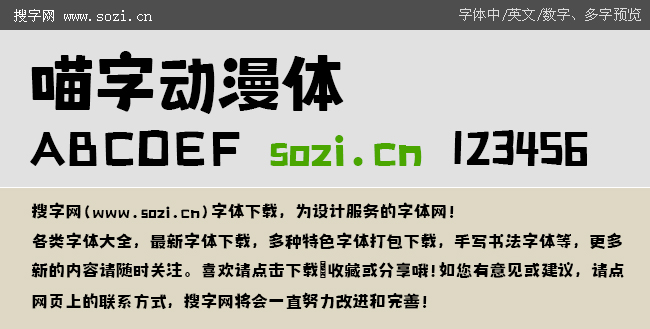
喵字動(dòng)漫體
搜字網(wǎng)提供一款喵字動(dòng)漫體中文藝術(shù)字體下載,喵字動(dòng)漫體是一款卡通風(fēng)格的藝術(shù)字體,該字體整體強(qiáng)調(diào)輕微的“律動(dòng)感”,力求在傳統(tǒng)架構(gòu)的標(biāo)題字基礎(chǔ)上追求“松動(dòng)”的排版效果。此款字體適用于海報(bào)設(shè)計(jì)、報(bào)刊雜志標(biāo)題、廣告設(shè)計(jì)等領(lǐng)域。